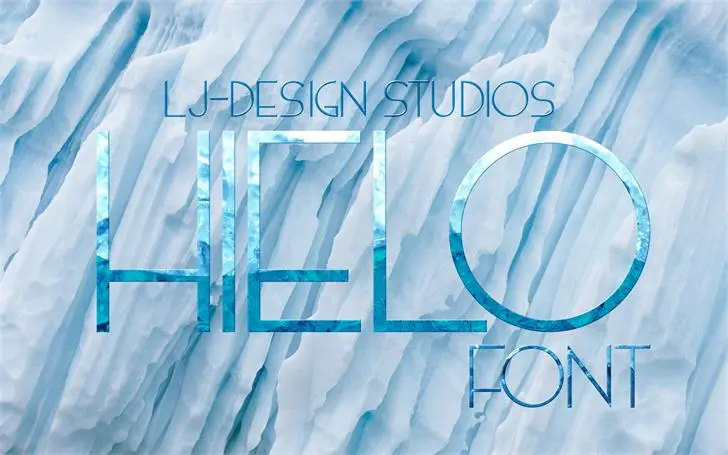
A fonte HIELO é uma criação única de Hamilton para a categoria de fonts de terror. Perfeita tanto para ilustrações assustadoras quanto para textos sobrenaturais, essa font oferece um tom sombrio e intenso que se encaixa perfeitamente com qualquer projeto no estilo horror. Se você está procurando por uma font que destaque suas criações góticas ou terroristicas com elegância e poder, HIELO é a escolha certa. Para acessar mais detalhes sobre como adquirir o produto, visite http://ljdesignstudios.es.tl/Hielo-Font.htm ou entre em contato através dos emails indicados na descrição original. Não hesite em seguir Hamilton para ver novas criações e atualizações.